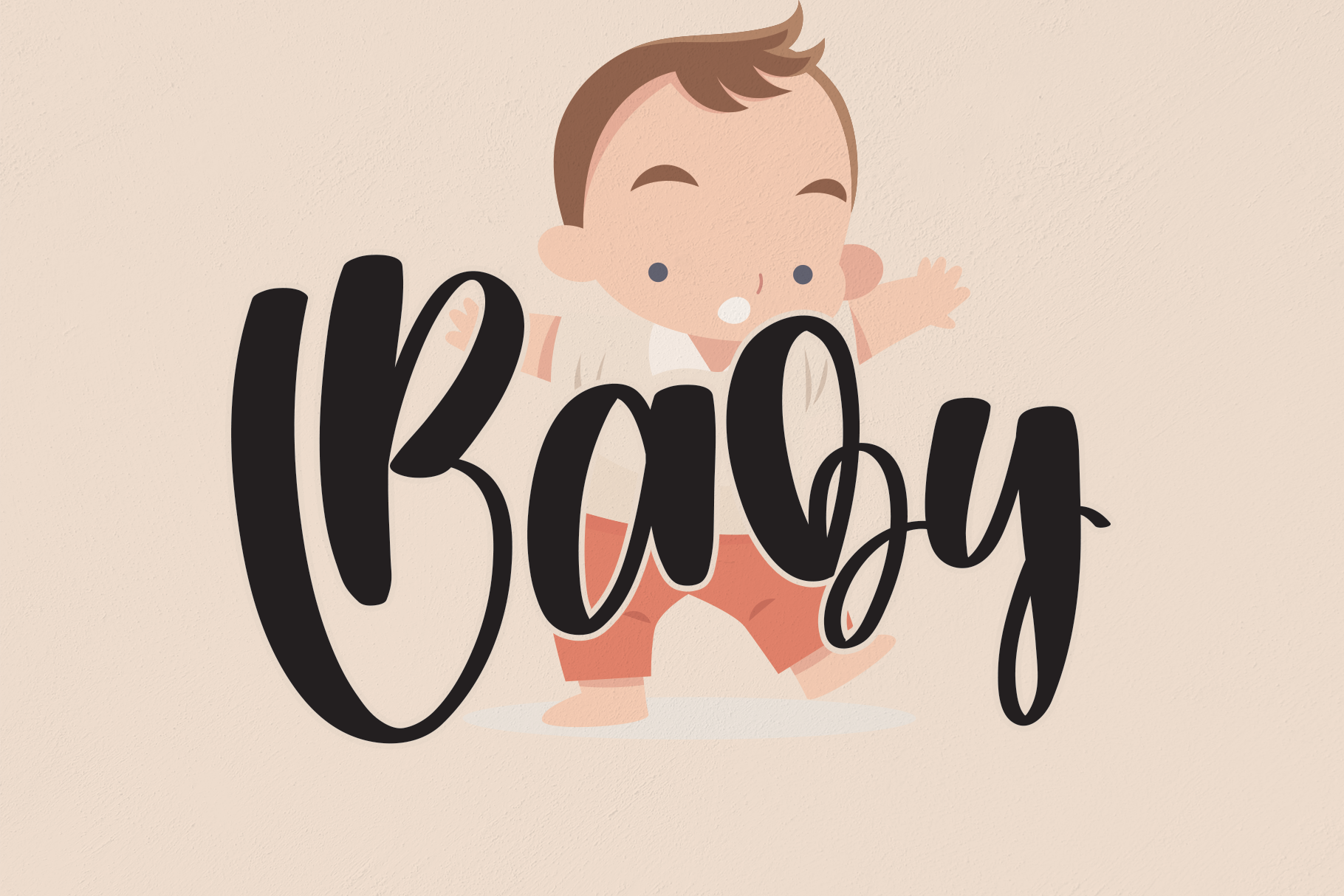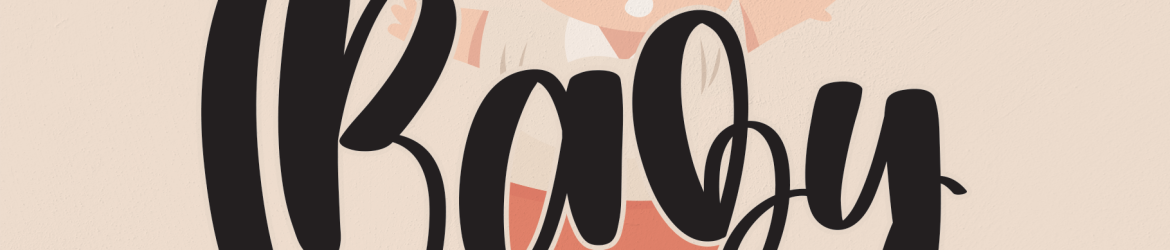
Baby Font – Download Grátis
Esta é uma delicada e natural fonte escrita a mão. Perfeita para qualquer aplicação visual onde desejar desenvolver marcações, embalagens de produtos, convites, citações, camisetas, rótulos, posters ou logotipos. É perfeitamente adaptável à sua necessidade, oferecendo um toque natural e delicado que adicionará uma autenticidade única aos seus projetos. Seja para criar elementos de design minimalistas ou mais elaborados, a Baby Font é a escolha certa. Ideal tanto para designers profissionais quanto iniciantes que buscam dar vida a suas ideias com um touch único e natural.